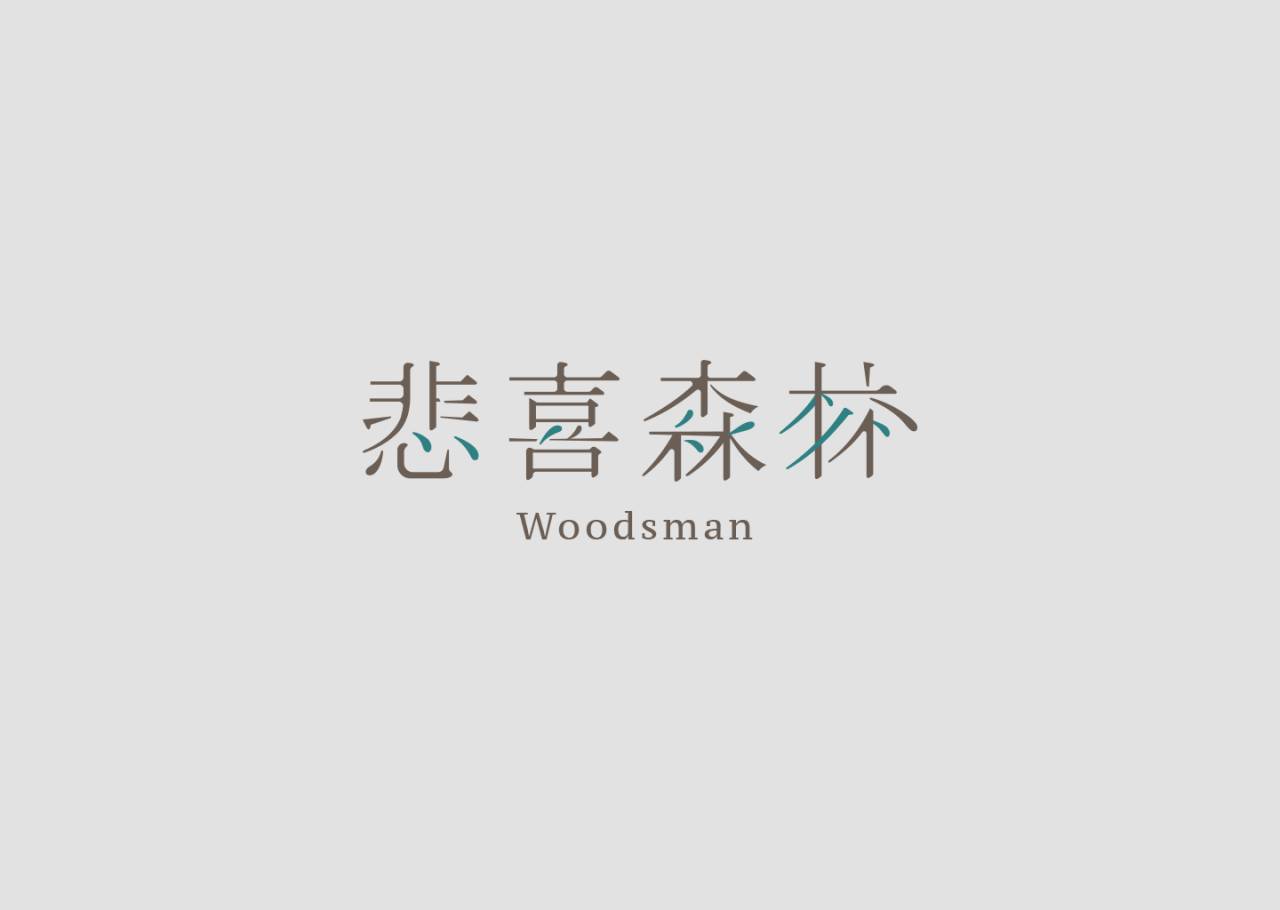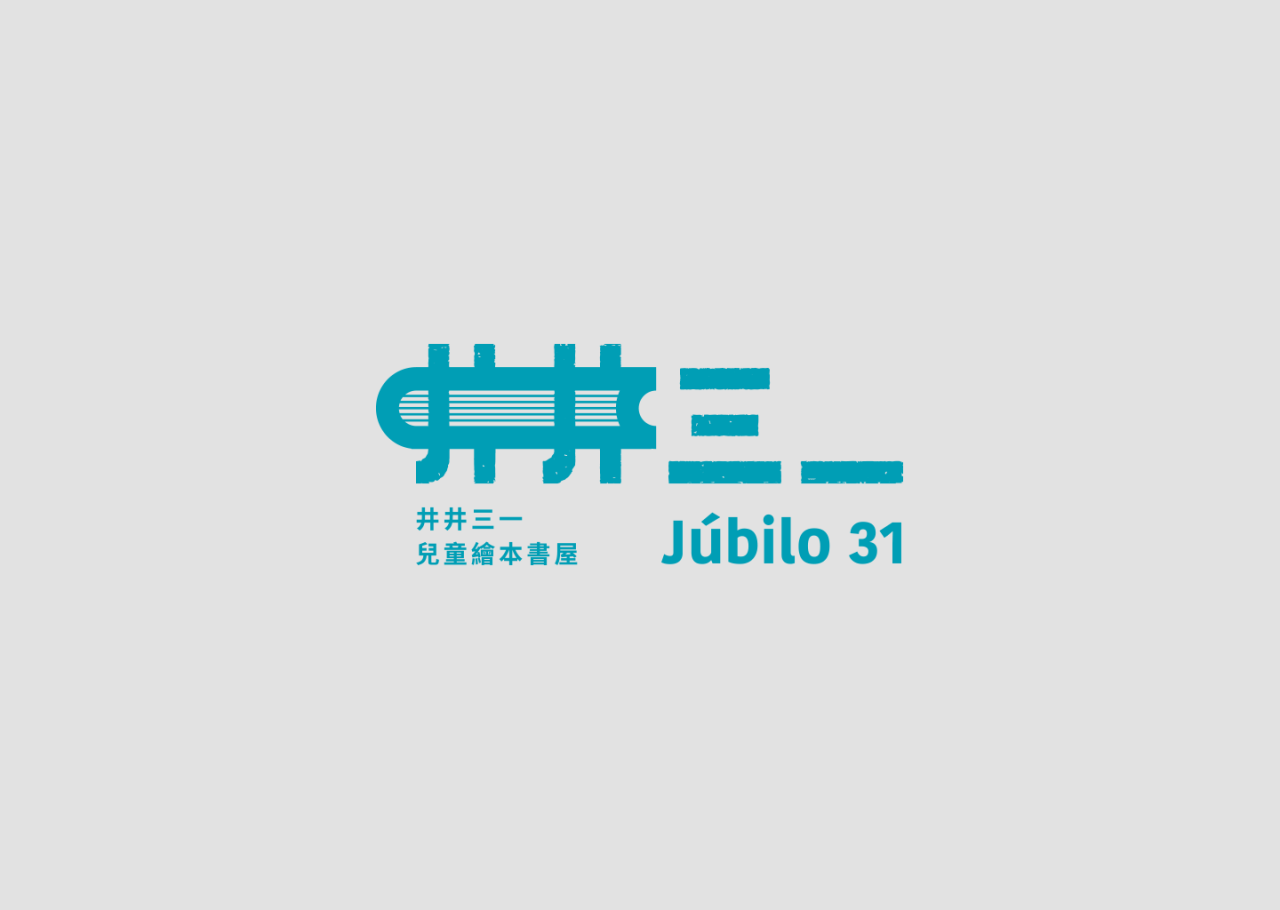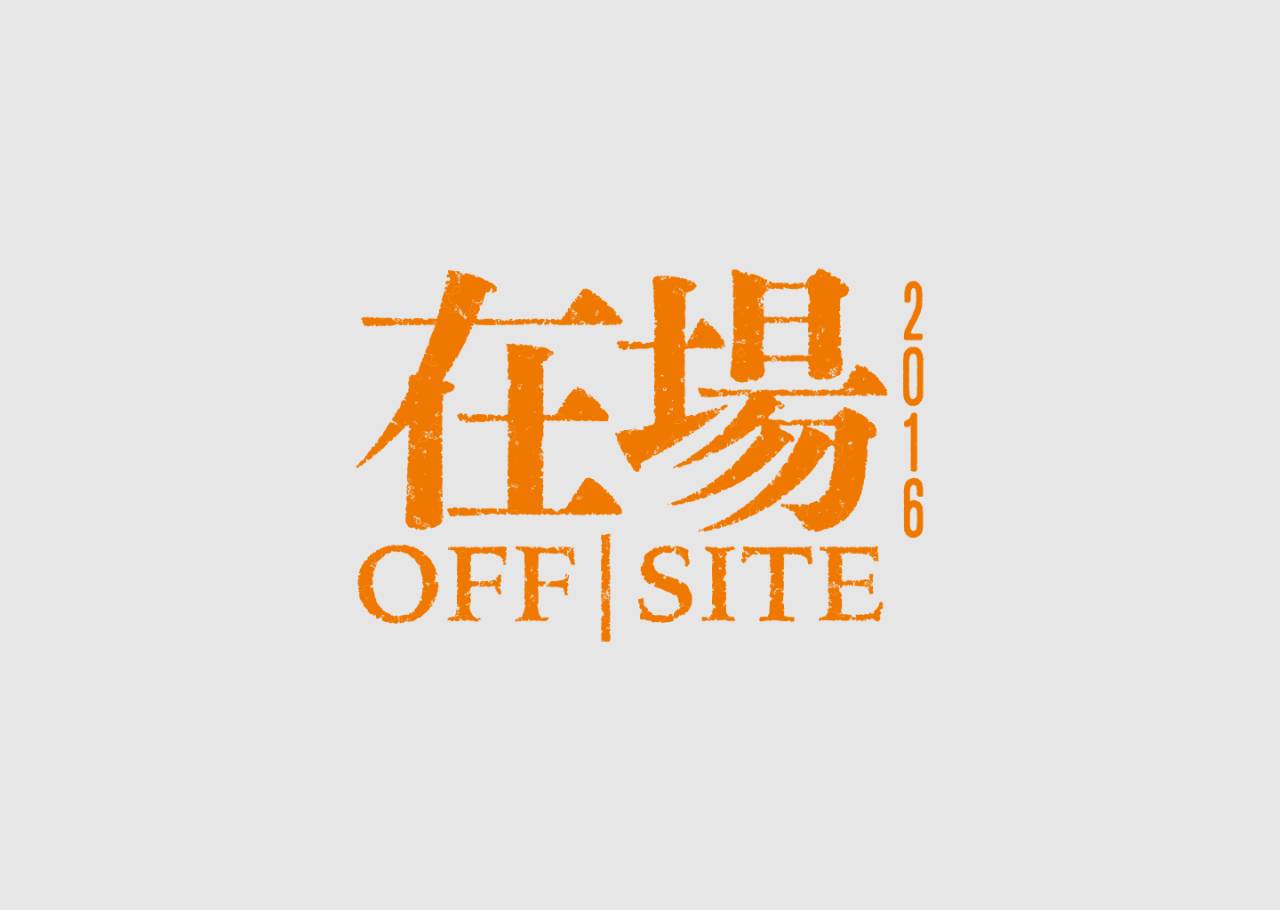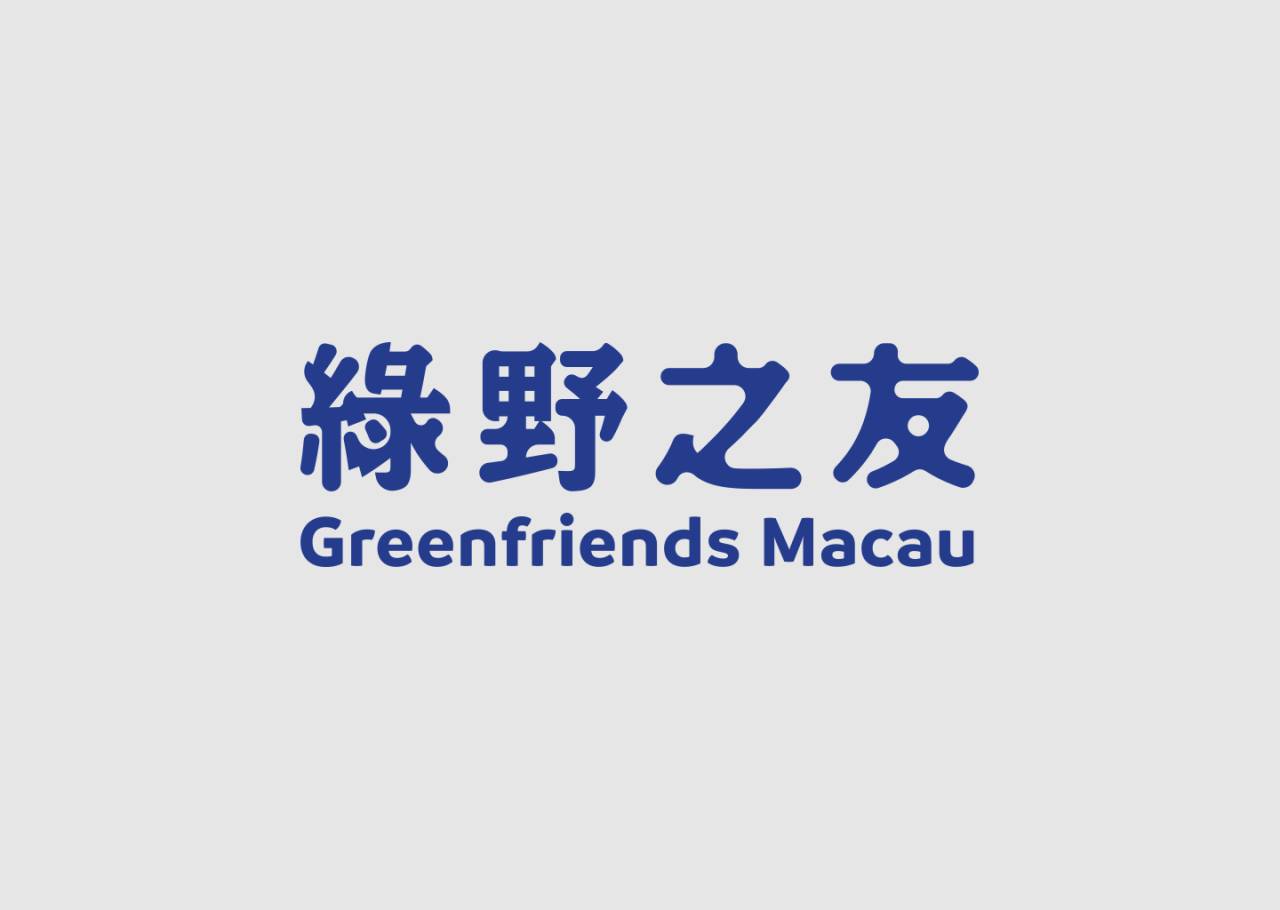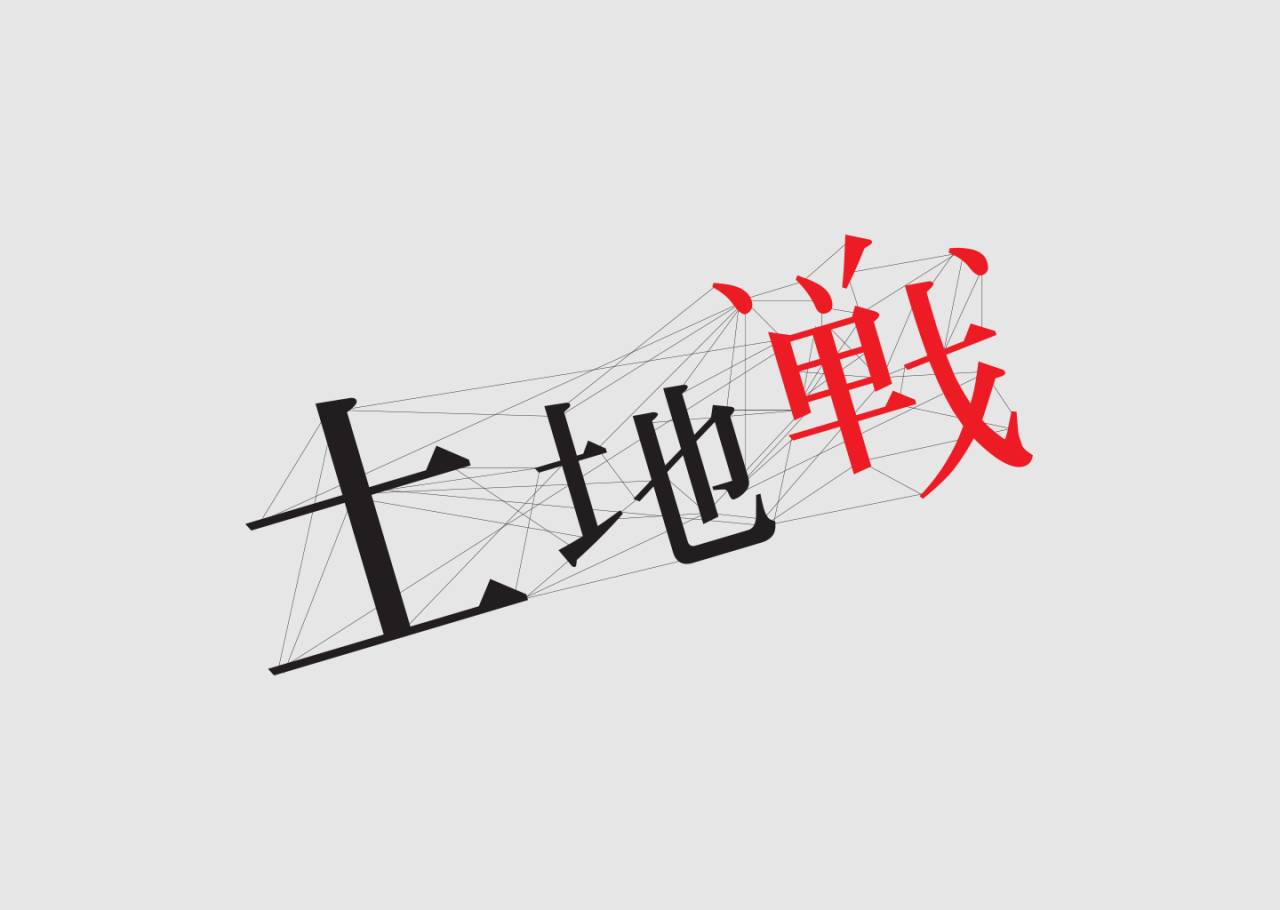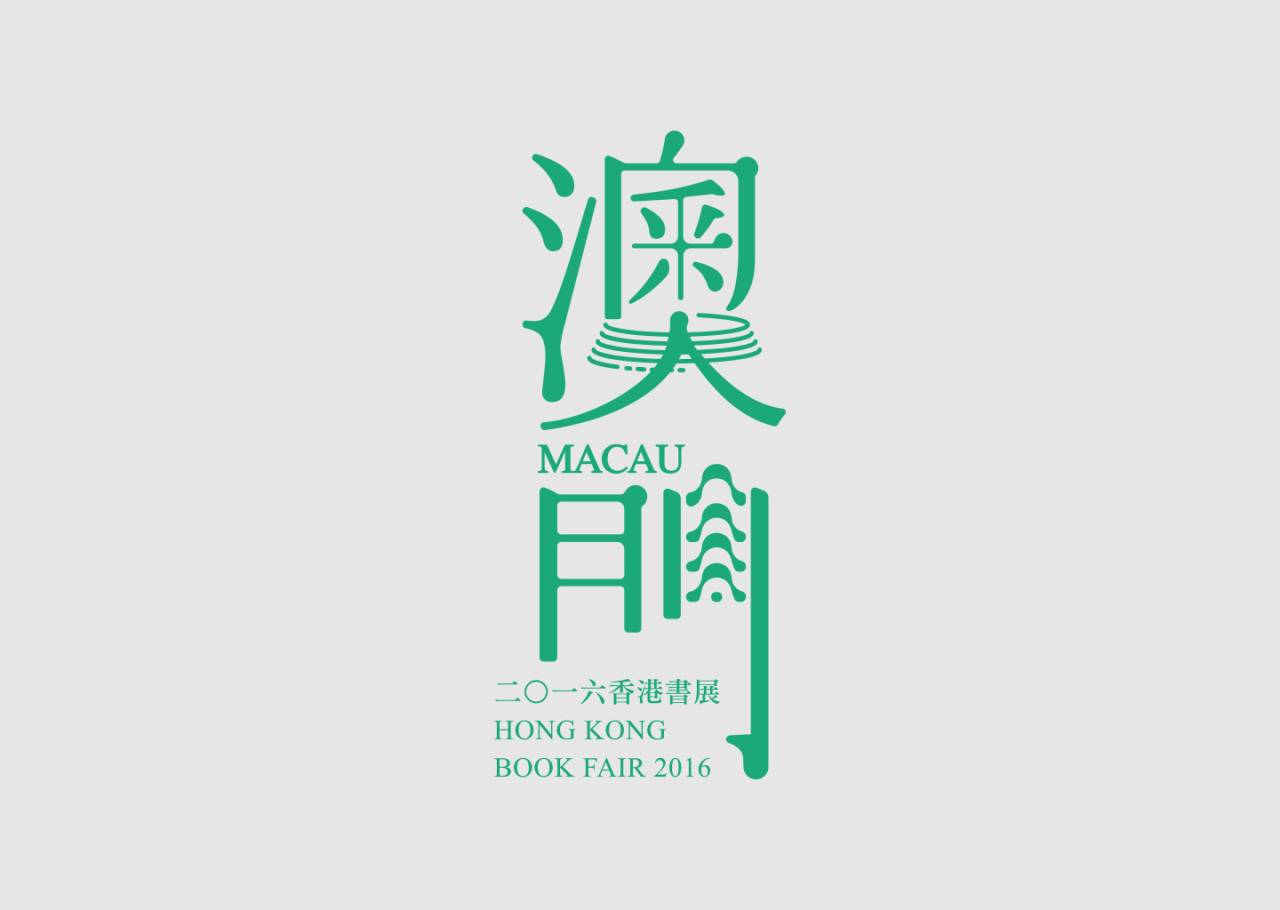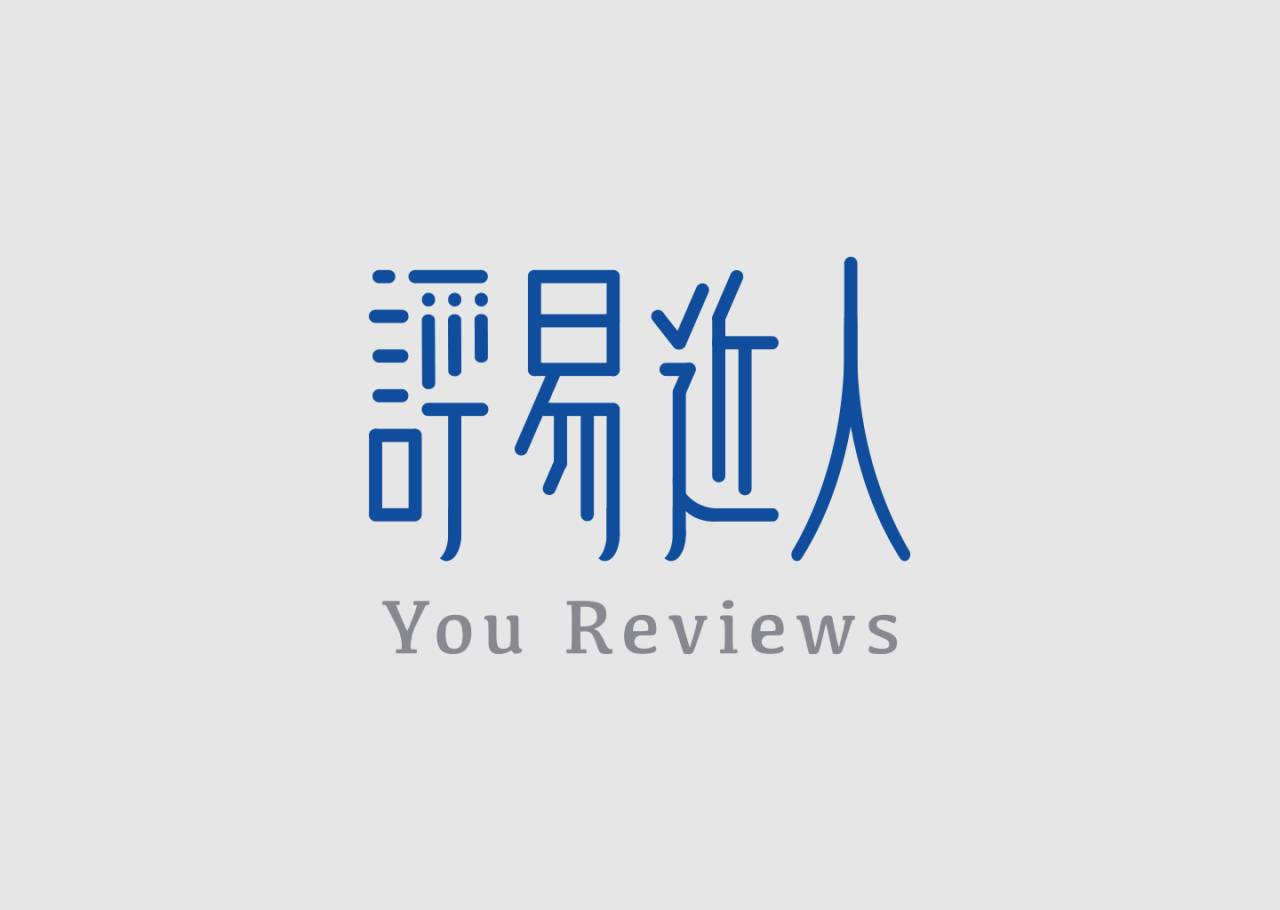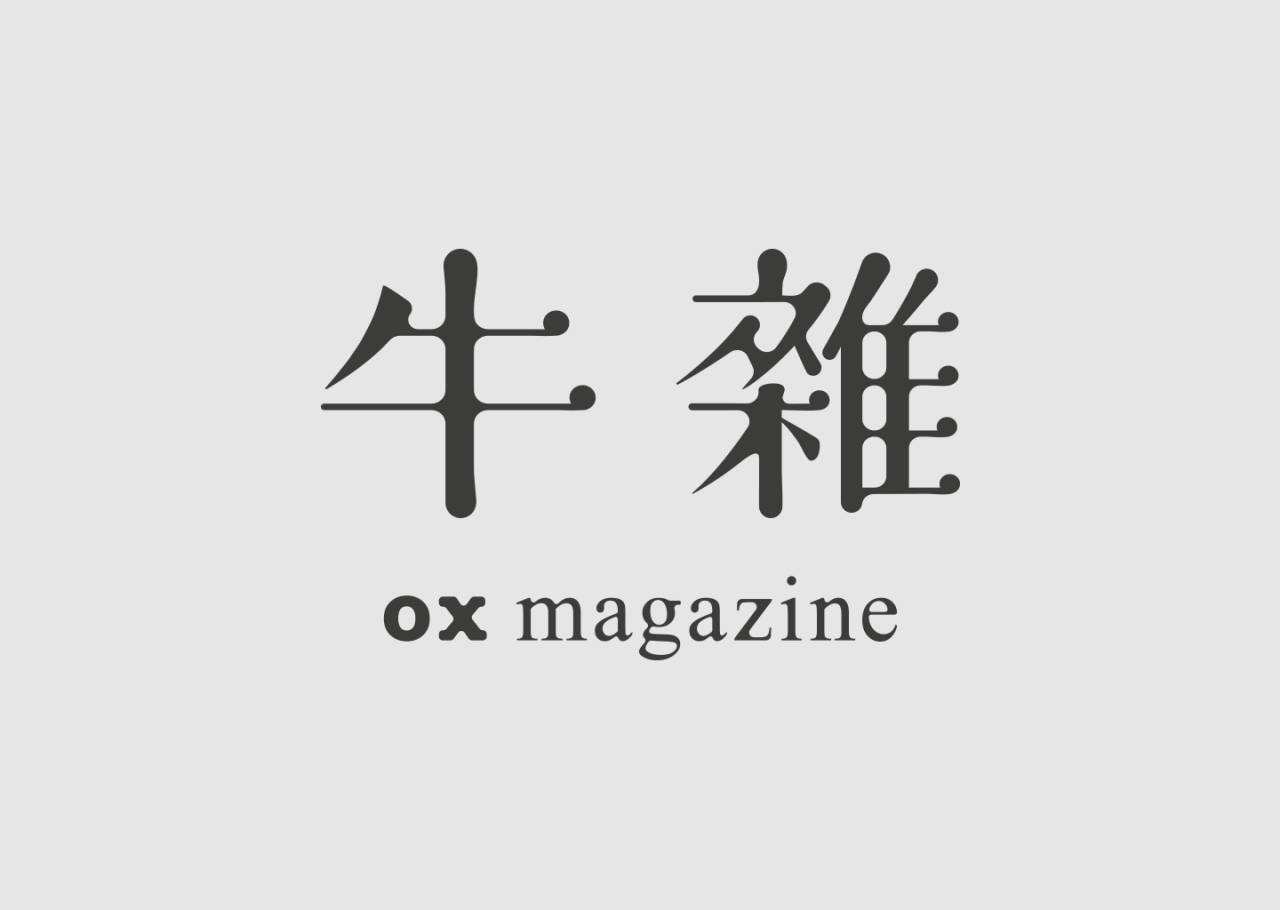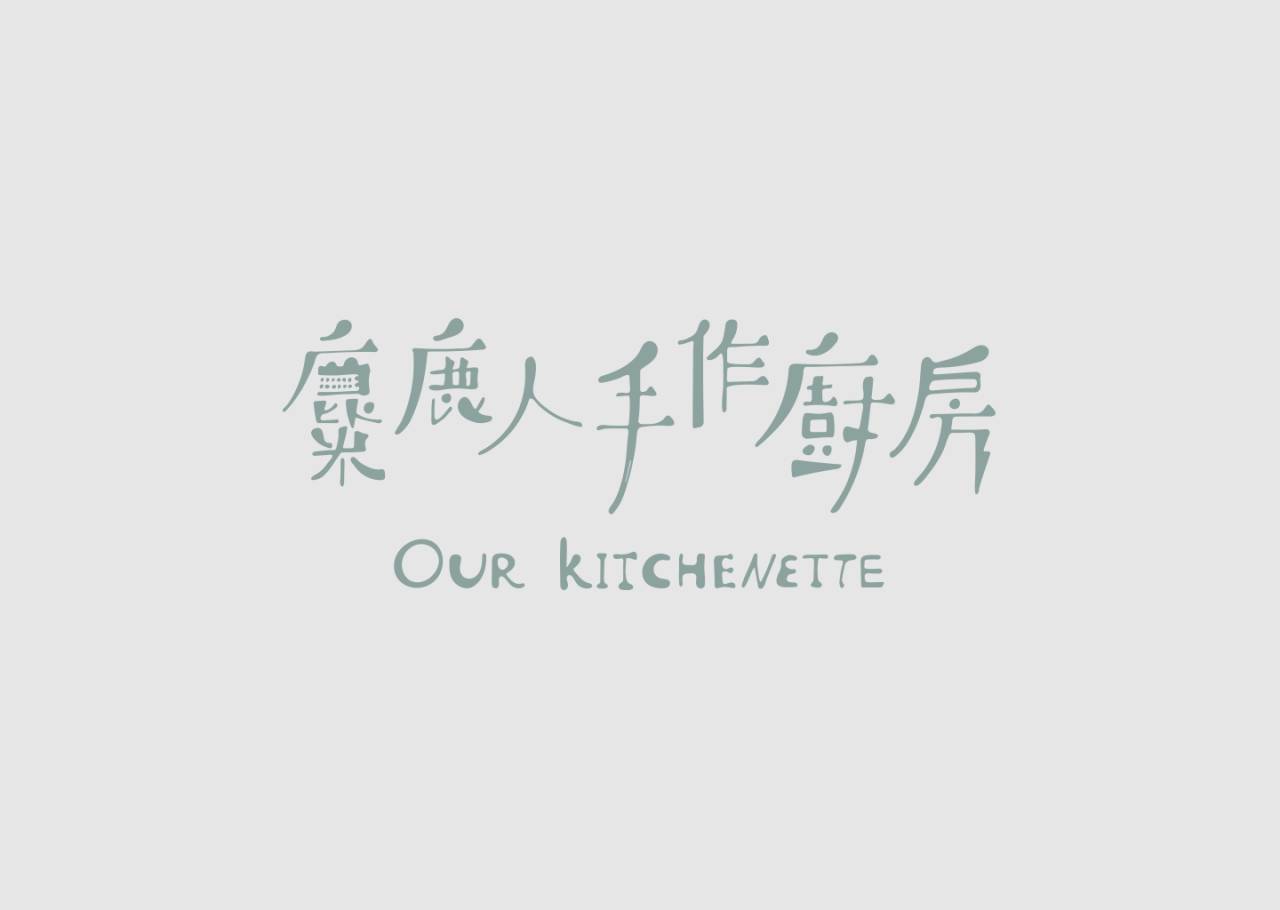
澳门设计师 Ck Chiwai Cheang 的汉字设计案例,时尚优美的字体设计案例
毕加索曾经说过,中国的每一个汉字本身就是一幅画。中文形体优美,内涵丰富,还自带象形、诗意的造型特点。但是总有人说用英文排版怎么着都好看,一放进中文就土气起来,那还不是因为你不会用汉字的缘故!一起来看看澳门设计师 Ck Chiwai Cheang 的汉字设计~